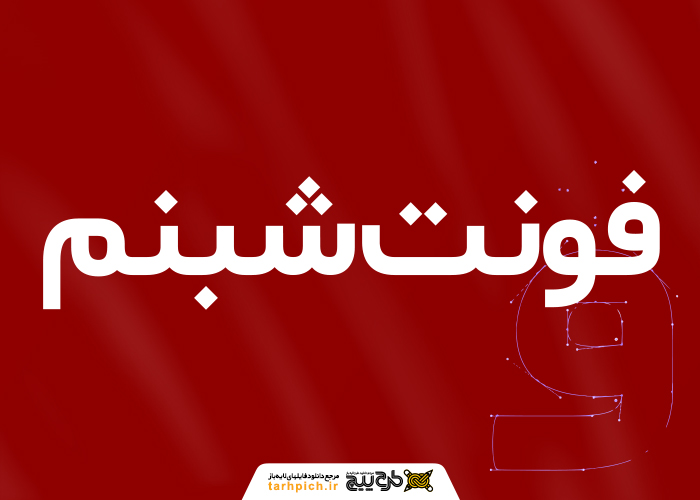
فونت شبنم
فونت رایگان شبنم از مجموعه فونت های آزاد می باشد همین طور نوع فونت طراحی وب و متن می باشد.فونت شبنم یکی ازبهترین  فونت های فارسی برای دوست داران فونت ساده در سبک فونت یکان است .آخرین نسخه فونت شبنم توسط شادروان صابر  راستی  کردار طراحی و ساخته شده است.